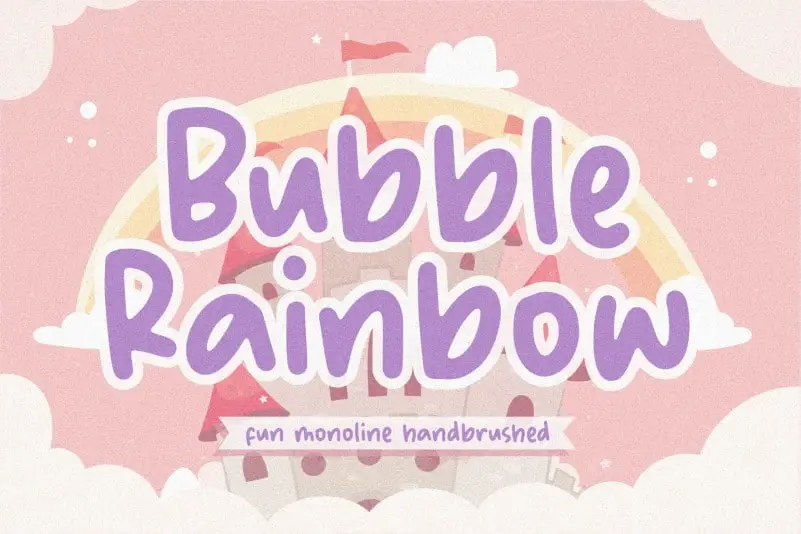
Bubble Rainbow Handbrushed Font – Fonte Grátis
Bubble Rainbow Handbrushed Font
A fonte ‘Bubble Rainbow Handbrushed Font’ do designer balpirick é perfeitamente adaptada para uma variedade de projetos criativos em arte digital. Com sua característica de letras borradas e cores vibrantes, essa fonte brochurizada vai adicionar um toque único a qualquer projeto gráfico, seja ele para embalagens de produtos, campanhas de marca, revistas ou até mesmo para expressar frases sobre um fundo. Suas cores de borboleta cintilante e forma brilhante trazem uma sensação de festa e diversão ao seu design. Não perca essa fonte icônica para aproveitar suas infinitas possibilidades criativas, seja para a sua próxima campanha social ou para criar um convite de casamento cheio de glamour.